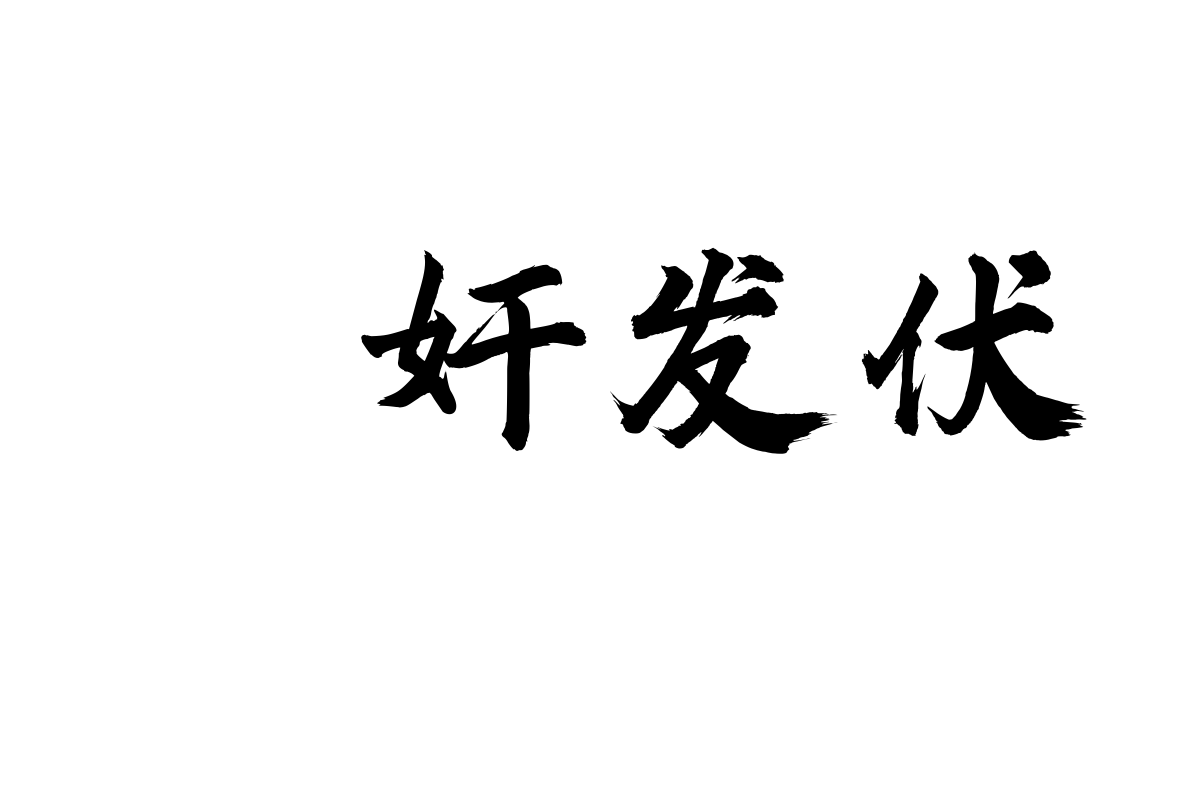
文道破浪体是一种书法字体,由书法家文道先生创造。该字体以其独特的风格和韵味而闻名,具有以下特点:
1. 字形结构:文道破浪体的字形结构独特,笔画流畅自然,富有变化。每个字的笔画都有其独特的形状和弧度,使得整体字形更加美观大方。
2. 笔画风格:文道破浪体的笔画风格独特,既有传统的楷书笔法,又有现代的创意元素。笔画粗细适中,既有力度感,又不失轻盈感,给人以美的享受。
3. 字体韵味:文道破浪体具有浓厚的书法韵味,无论是书写还是欣赏,都能让人感受到一种独特的艺术魅力。字体中的线条、结构和布局都充满了艺术感,让人陶醉其中。
4. 适用范围:文道破浪体适用于各种场合,如书法、海报、广告等。它的字体大小、粗细、颜色等都可以根据需要进行选择和调整,以满足不同场景的需求。
总之,文道破浪体是一种独具特色的书法字体,以其独特的风格和韵味赢得了广泛的赞誉。无论是用于个人创作还是商业用途,文道破浪体都是一款值得尝试的优秀字体。